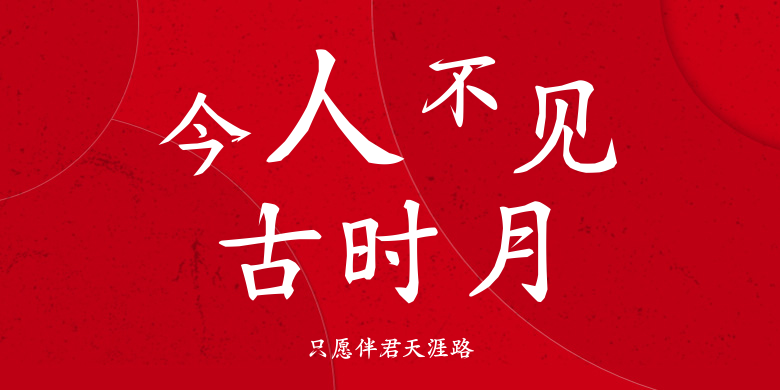
只愿伴君天涯路
只愿伴君天涯路,这款字体结构工整、笔画清晰,兼顾美观与易读性,适用于标题、正文、海报、包装、LOGO 等多种场景。字形优雅稳定,风格百搭耐看,适配日常排版与创意设计,让文字呈现更舒适、更具质感。只愿伴君天涯路一笔一画,皆是细节,以均衡的比例、流畅的线条打造舒适视觉体验,字形端正大气,风格简约现代。无论是商业设计、品牌宣传还是日常排版,都能轻松驾驭,让文字更有格调与力量。只愿伴君天涯路字体下载。